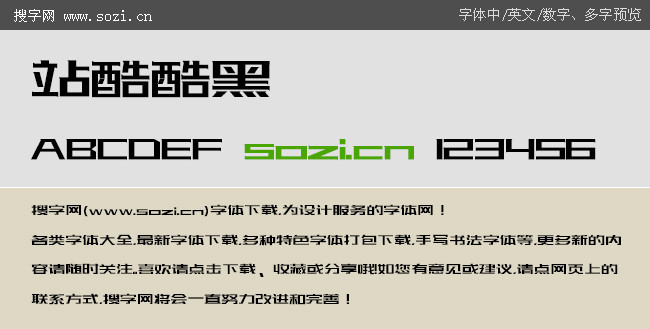
站酷酷黑
搜字網(wǎng)提供一款站酷酷黑中文字體下載,該字體由胡曉波發(fā)起,字游工作室成員進(jìn)行基礎(chǔ)字形設(shè)計(jì),胡曉波設(shè)計(jì)班十名學(xué)員共同設(shè)計(jì)完成。字形筆畫粗獷有力、用寬扁型的字面構(gòu)建出厚重的字體形態(tài),筆畫細(xì)節(jié)上的修飾既增強(qiáng)了字體的設(shè)計(jì)感,又讓字體多了一些小小的精致感。免費(fèi)授權(quán)所有設(shè)計(jì)師使用(可用于任何商業(yè)范圍)。